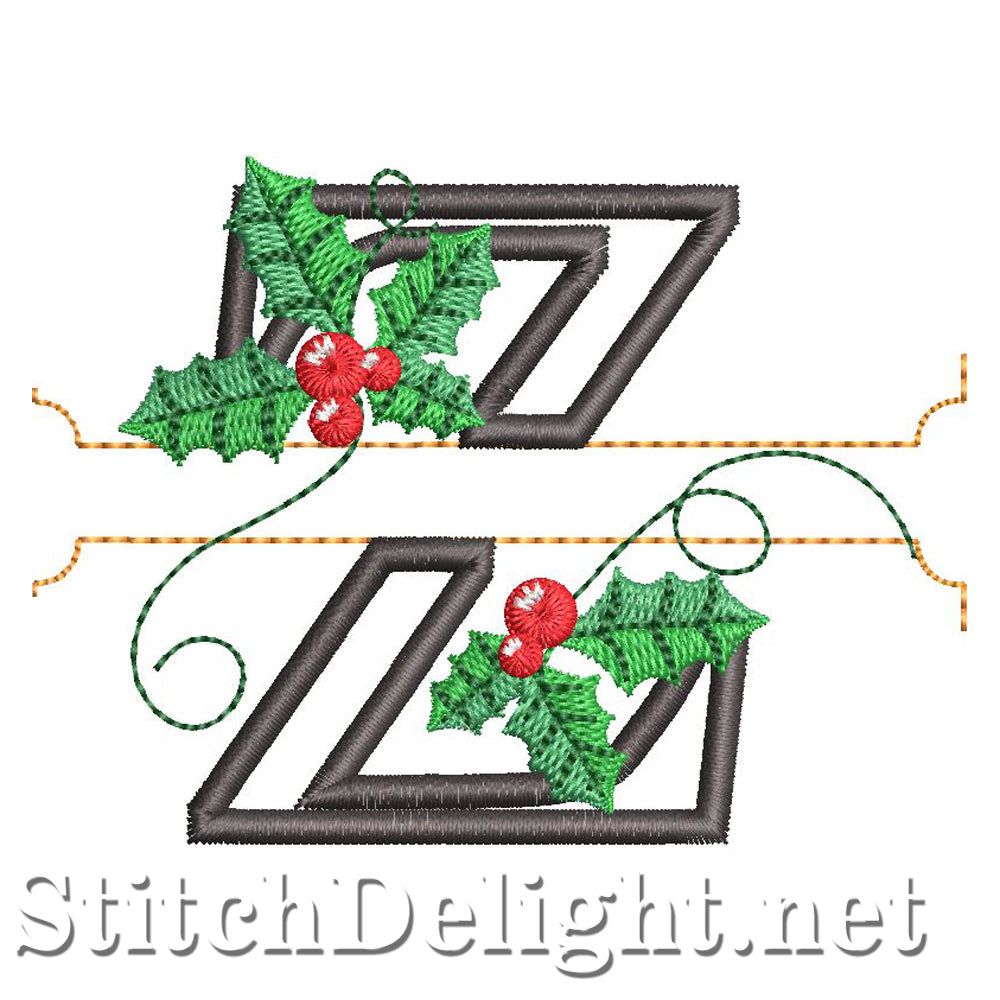
HOE0037 Festive Holly Police Z
Il n'est jamais trop tôt pour préparer ces décorations de Noël pour les fêtes de fin d'année. Cette belle lettre unique avec des feuilles de houx sur un fond rose doux est parfaite pour les taies d'oreiller, les couvertures, les bavoirs, etc. Conçue pour s'adapter au cerceau 4x4.